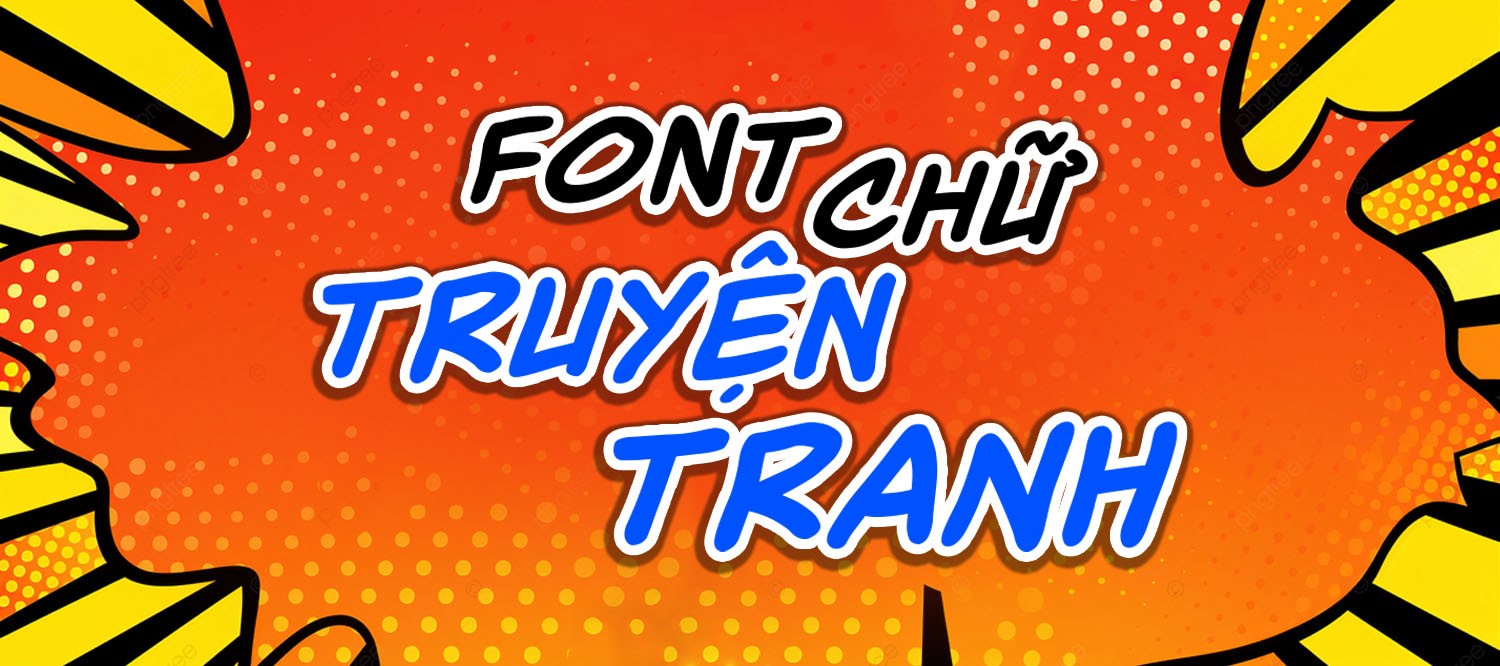
![[Tải xuống] Kho font chữ truyện tranh manga, teddy bear và comic mới nhất 2025](https://cdn.s99.vn/blog/font-truyen-tranh-manga-7.jpg)
Trong lĩnh vực thiết kế truyện tranh, việc sử dụng các font chữ phù hợp với nội dung của câu chuyện vô cùng quan trọng. Nó quyết định tới nội dung của câu chuyện được truyền tải đến người đọc. Font chữ không chỉ giúp người đọc dễ dạng, mà nó còn thể hiện được cảm xúc câu chuyện, tính cách của các nhân vật trong tác phẩm. Các font chữ truyện tranh dành cho các dòng manga Nhật Bản hay các chủ đề dễ thương như font teddy bear cho truyện thiếu nhi, việc sử dụng font phù hợp với nội dung sẽ mang lại sự chuyên nghiệp cho cuốn truyện. Trong bài viết này S99 chia sẻ tới các bạn kho font truyện tranh bao gồm font manga và font teddy bear cũng như cách sử dụng các font chữ sao cho hiệu quả.
Font manga là các kiểu chữ được sử dụng trong lĩnh vực truyện tranh Nhật Bản. Manga là một trong những thể loại truyện tranh được ưa chuộng nhất thế giới, với các nét riêng biệt về nội dung và hình ảnh. Để giúp các cuốn truyện hấp dẫn và truyền tải tốt các nội dung, cảm xúc của các nhân vật, font manga là lựa chọn không thể thiếu trong các cuốn truyện.
Các font manga ngoài việc đáp ứng được tính dễ đọc thì còn cần phải thể hiện được khả năng truyền tải cảm xúc của nhân vật trong câu chuyện. Ví dụ khi hình ảnh minh họa các nhân vật thể hiện sự tức giận, các font chữ sẽ phải lớn và đậm hơn. Hay khi các nội dung đối thoại nhẹ nhàng thì cần sử dụng các font chữ nhỏ đều dễ đọc. Những yếu tố này sẽ giúp người đọc có thể hòa mình vào các câu chuyện của tác giả.
Trong công đồng thiết kế truyện tranh manga, một số font manga được ưa thích và sử dụng khá nhiều nhờ sự linh hoạt và truyền tải thông điệp tốt. Dưới đây là hình ảnh font manga trong bộ 80 font được S99 chia sẻ miễn phí tới các bạn
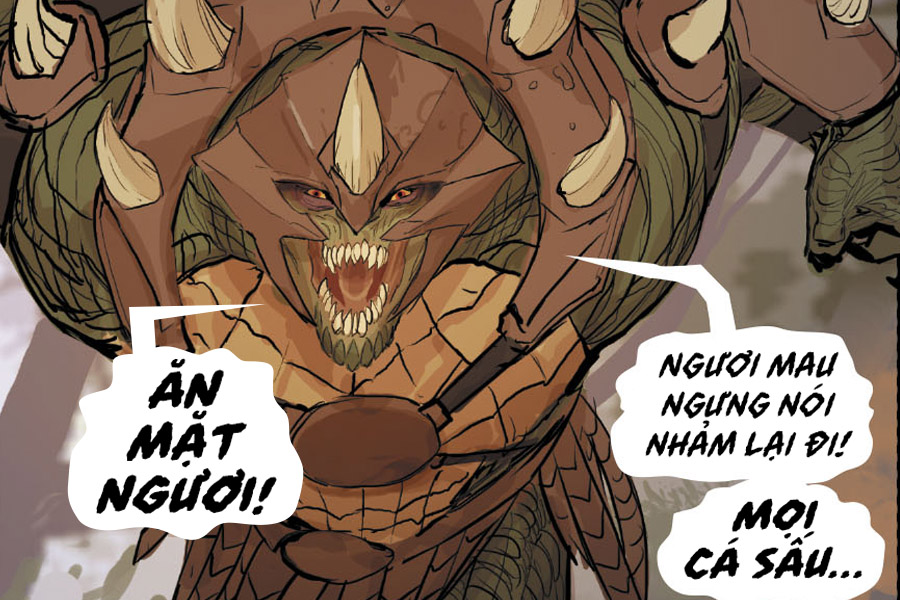
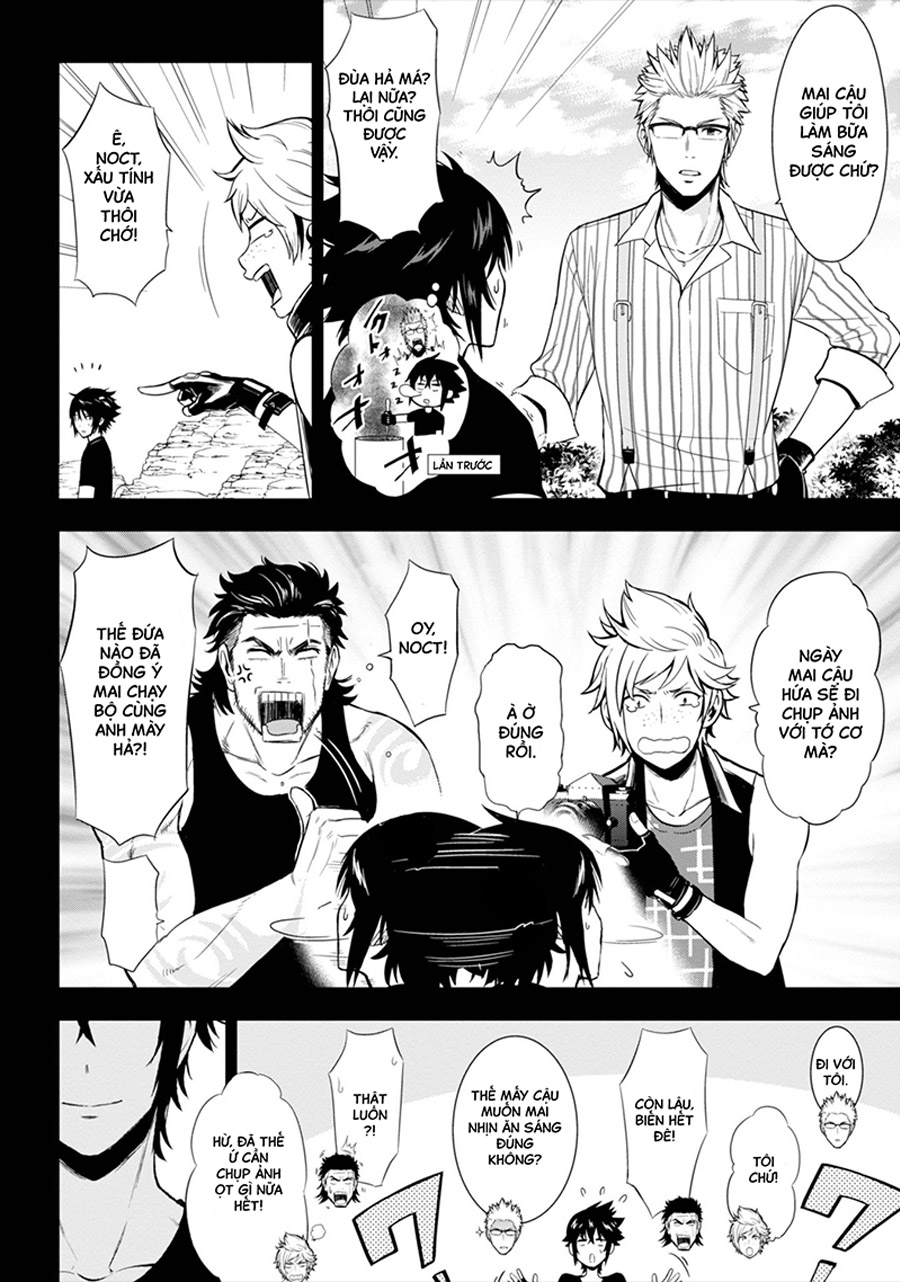
Việc sử dụng font manga cho các cuốn truyện phụ thuộc khá nhiều vào thể thoại truyện mà tác giả đang viết. Đối với các thể loại truyện tranh hành động, thám hiểm có phần kịch tính, chúng ta nên sử dụng các font chữ có nét đậm, mạnh mẽ để thể hiện tốt cảnh chiến đấu trong trong từng lời thoại của nhân vật. Ngược lại với các câu truyện có lời thoại tình cảm, nhẹ nhàng thì các font chữ nên sử dụng mềm mại, uyển chuyển để phù hợp với nội dung truyện.
Ngoài ra chúng ta cũng cần phải lưu ý một điều vô cùng quan trọng, đó là khả năng thích ứng của font với nhiều kích thước khác nhau. Font chữ phải thật sự dễ đọc ngay cả khi in với kích thước nhỏ. Điều này giúp trải nghiệm của người đọc không bị gián đoạn, nhất là với các loại truyện manga, người đọc sẽ có xu hướng đọc lướt qua rất nhanh. Một yếu tố nữa đó chính là màu sắc của các font chữ, bạn phải đảm bảo rằng màu sắc phải nổi bật và phù hợp với nền truyện.
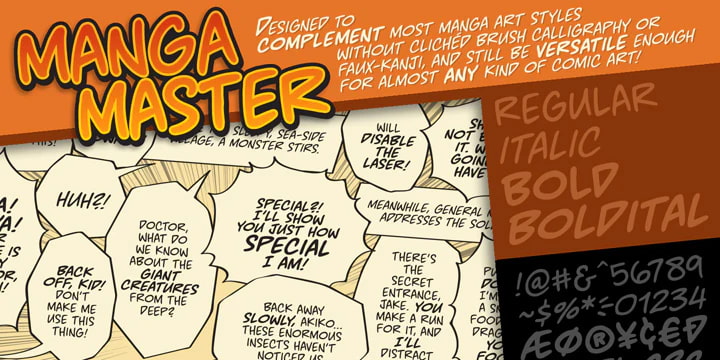
Font teddy bear là một dạng font có phong cách dễ thương, đáng yêu, các dạng font này thường sẽ được sử dụng trong thiết kế các thể loại truyện cho trẻ em hoặc những sản phẩm cần thể hiện sự cute và ngộ nghĩnh. Các đường nét trong font teddy bear thường được thiết kế mềm mại, căng tròn.
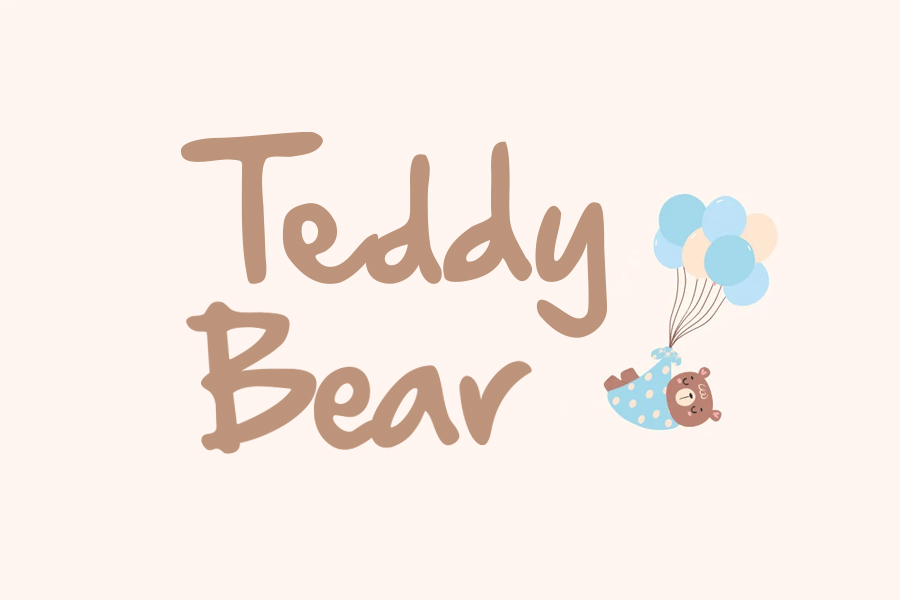
Các font teddy bear có nhiệm vụ tạo lên cảm giác vui vẻ, thân thiện, để giúp các bạn đọc nhỏ tuổi cảm thấy hấp dẫn và hứng thú hơn. Các font này thường được sử dụng đối với lời loại đơn giản, các câu nói ngắn gọn và nhẹ nhàng như lời chào hoặc các câu nói dễ thương.Ứng Dụng Của Font Teddy Bear Trong Thiết Kế Truyện Tranh
Ứng dụng của font teddy bear không chỉ giới hạn trong việc sử dụng cho truyện tranh thiếu nhi mà nó còn được dùng cho thiết kế các ấn phẩm như banner, bao bì, thiệp sinh nhật.
Đối với truyện tranh font teddy bear thường được được sử dụng trong các cảnh hài hước, những đoạn hội thoại đơn giản của các nhân vật.
Một số font teddy bear nổi bật tại thư viện font chữ của S99 bạn có thể tham khảo để sử dụng cho các sản phẩm thiết kế của mình.
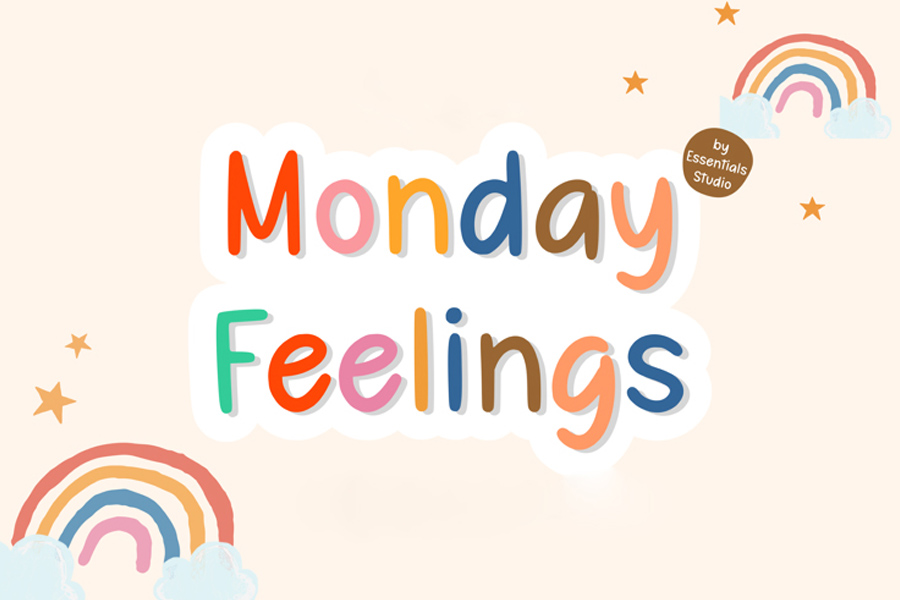
Tầm Quan Trọng Của Font Truyện Tranh
Đối với thể loại truyện tranh thì font chữ đóng một vai trò vô cùng quan trọng. Một font chữ phù hợp không chỉ giúp người đọc dễ dàng mà nó còn làm nổi bật tính cách của các nhân vật trong câu chuyện.
Để áp dụng font truyện tranh được hiệu quả chúng ta cần lưu ý tới những điều cơ bản như kích thước, độ hậm và màu sắc của font chữ. Font chữ cần được sử dụng phù hợp với từng đoạn nội dung để duy trì cảm xúc của độc giả. Chúng ta có thể thêm các hội thoại cho những hiệu ứng âm thanh để tạo nên sự hấp dẫn.
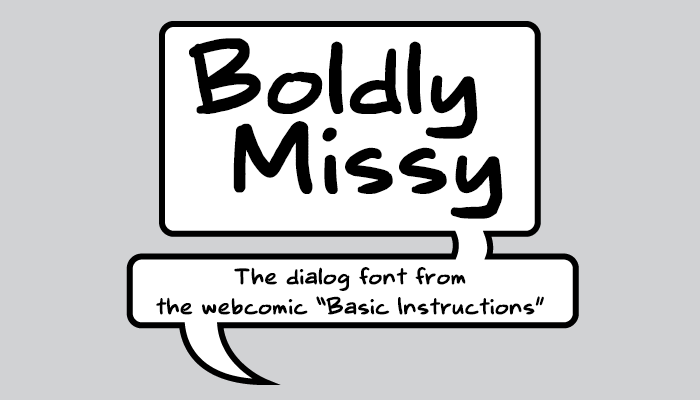
Qua bài chia sẻ trên hy vọng các bạn sẽ nhận thấy việc sử dụng font chữ cho thiết kế truyện tranh là vô cùng quan trọng. Font manga cho truyện tranh Nhật Bản thể hiện sự sống động và mạnh mẽ. Font teddy bear mang tới sự đáng yêu và dễ thương để phù hợp với các độc giả thiếu nhi. Hiểu và sử dụng được đúng các thể thoại font truyện tranh sẽ giúp tác giả truyền tải những nội dung được hiệu quả nhất tới người đọc. Hãy thử nghiệm và chọn ra font chữ phù hợp để nâng tầm tác phẩm của bạn!